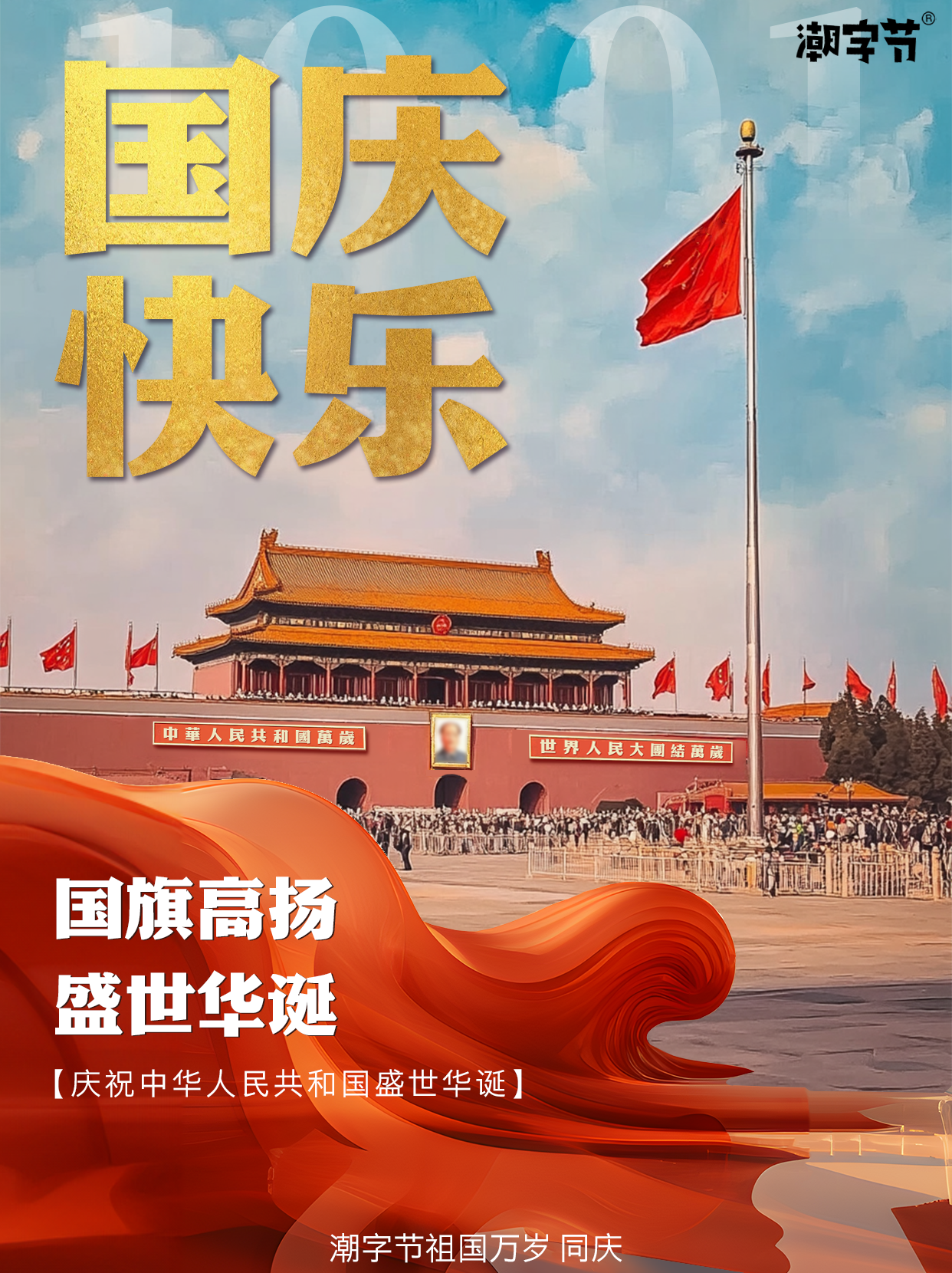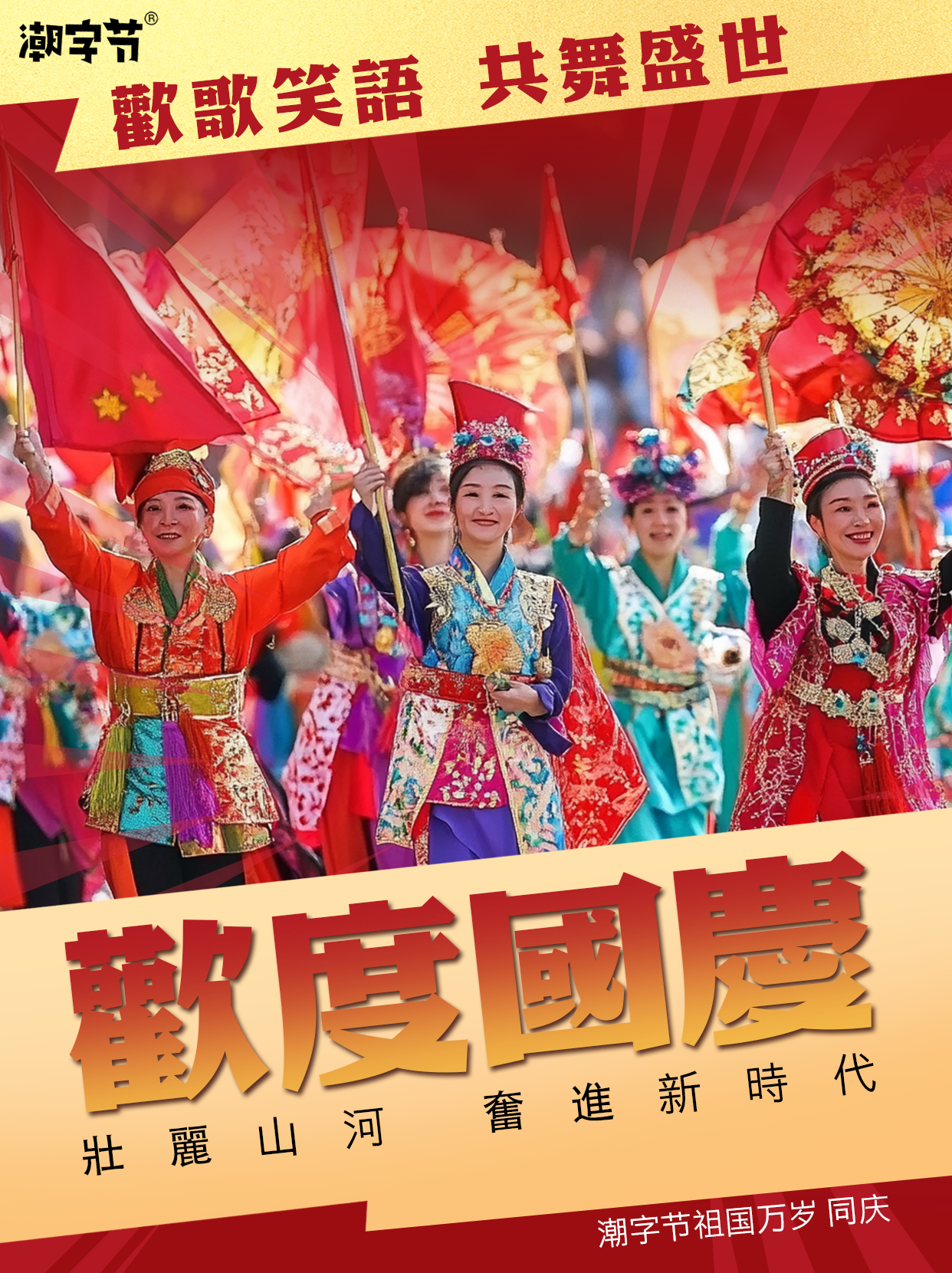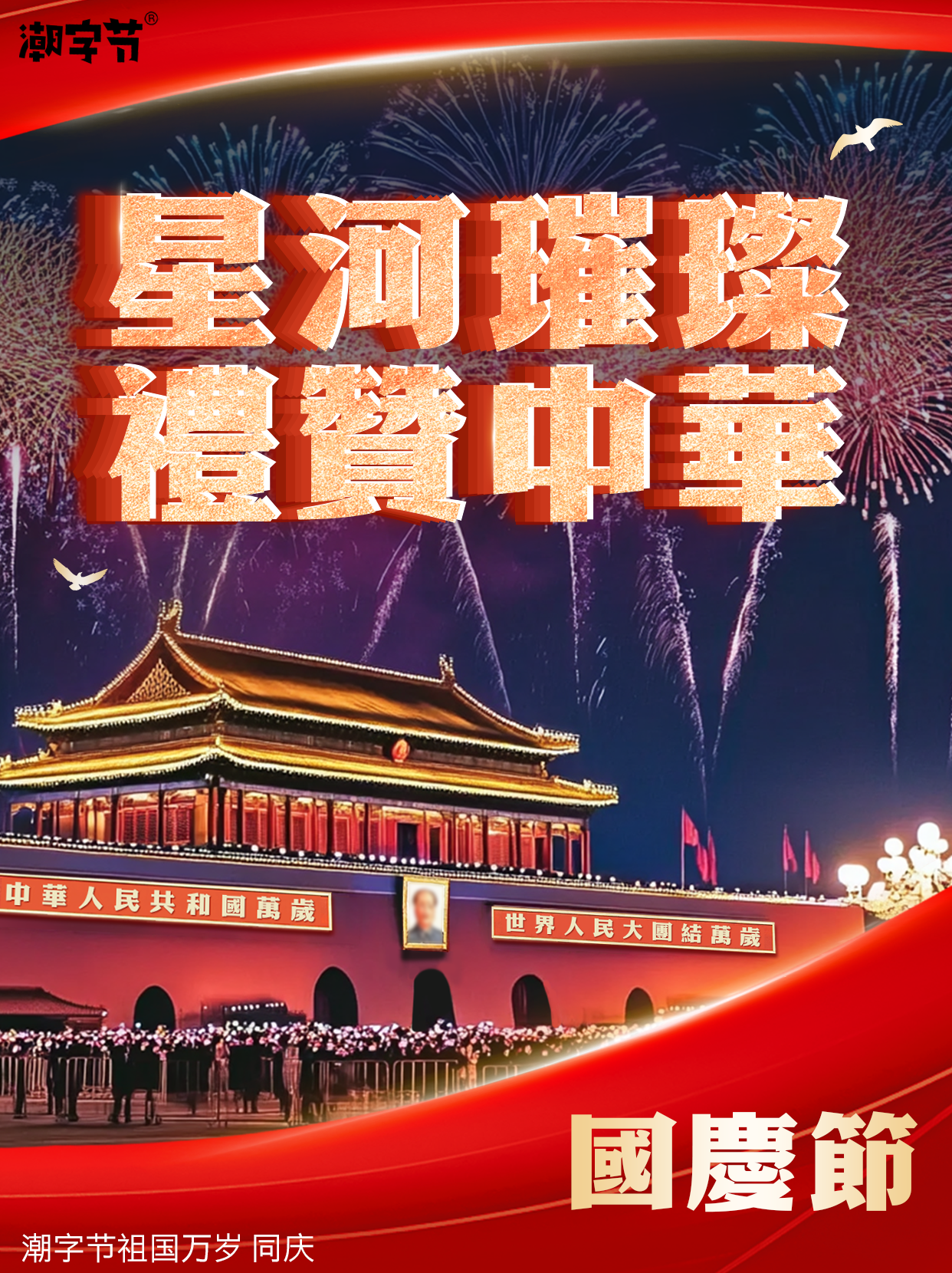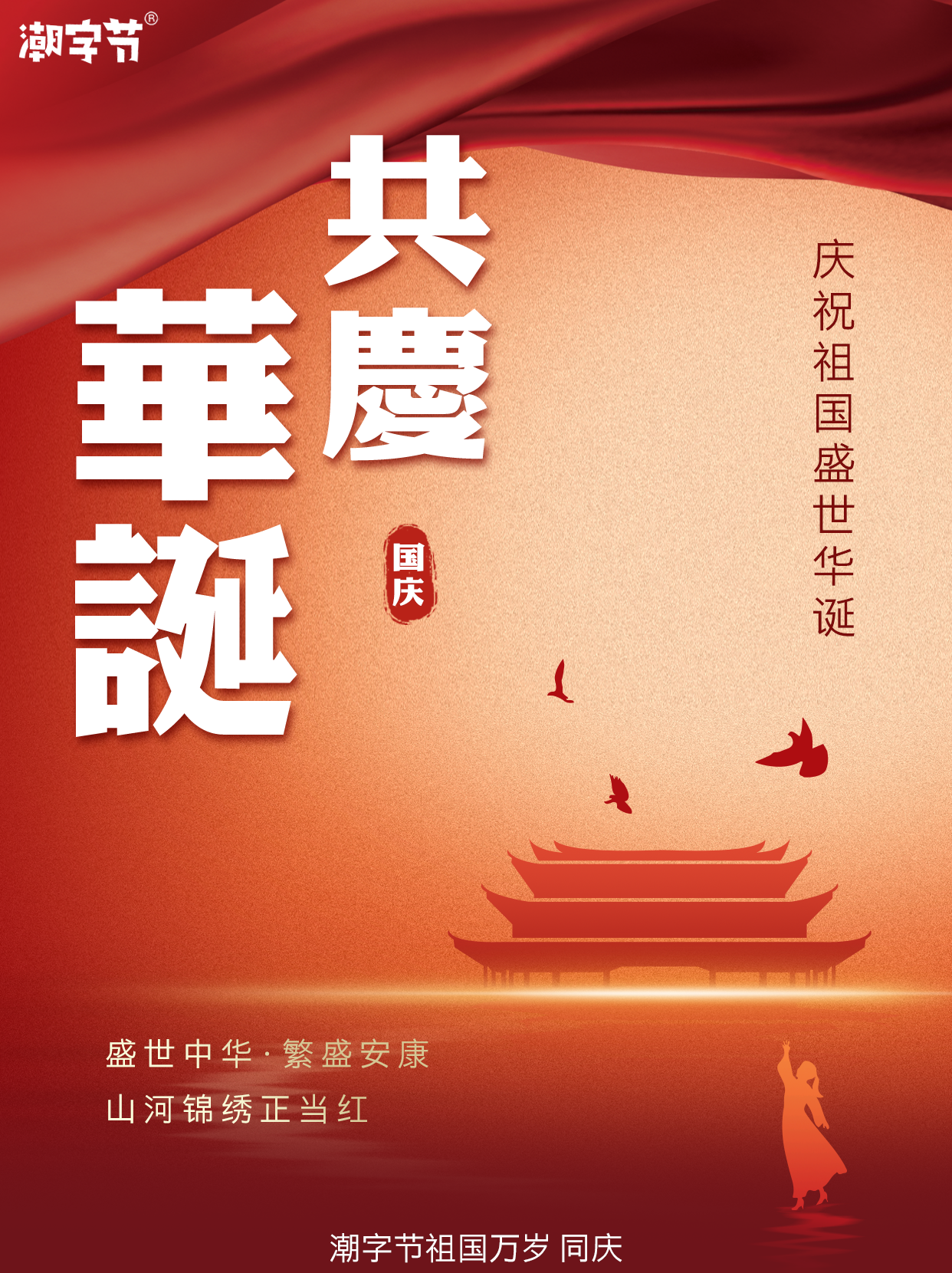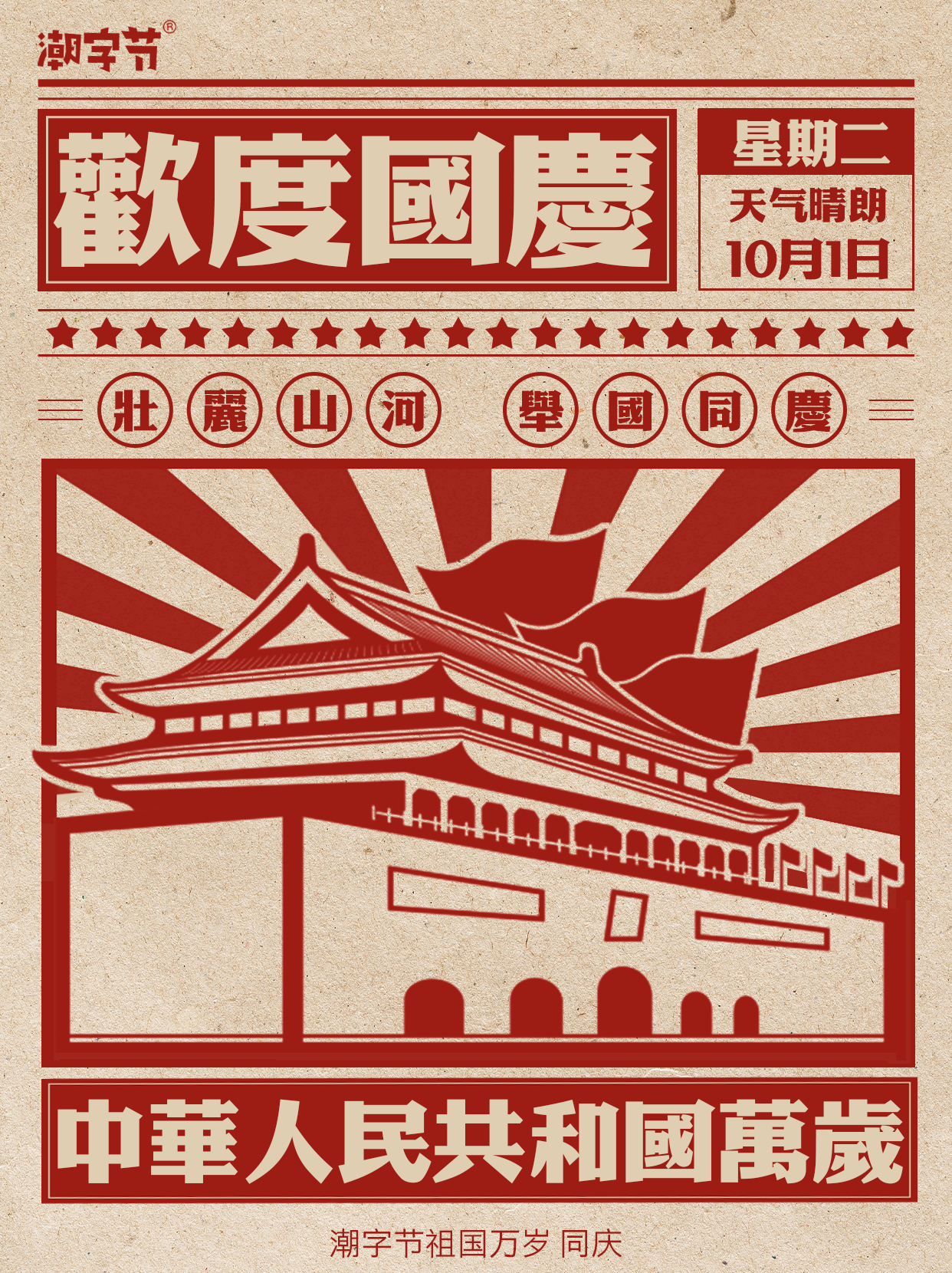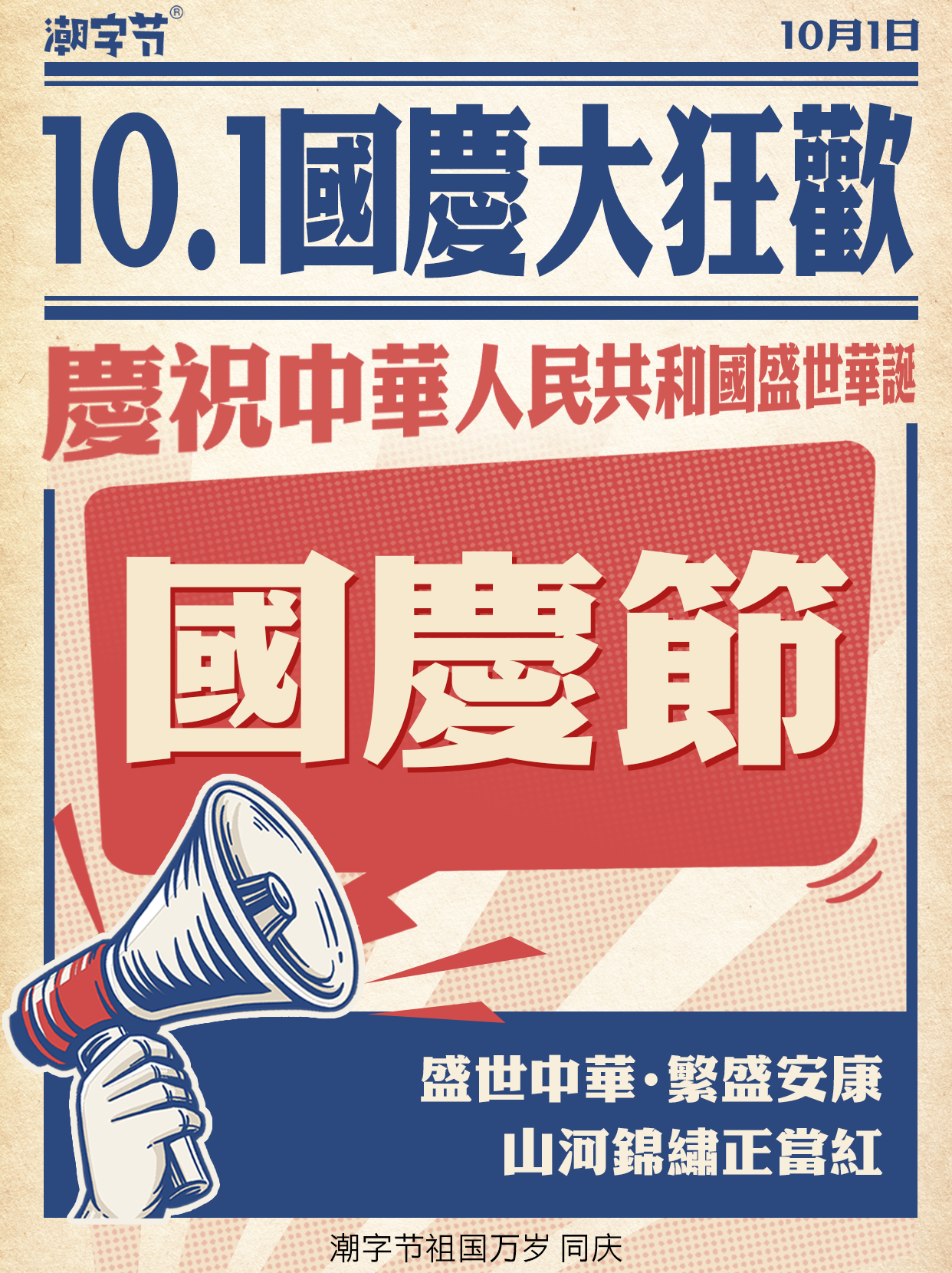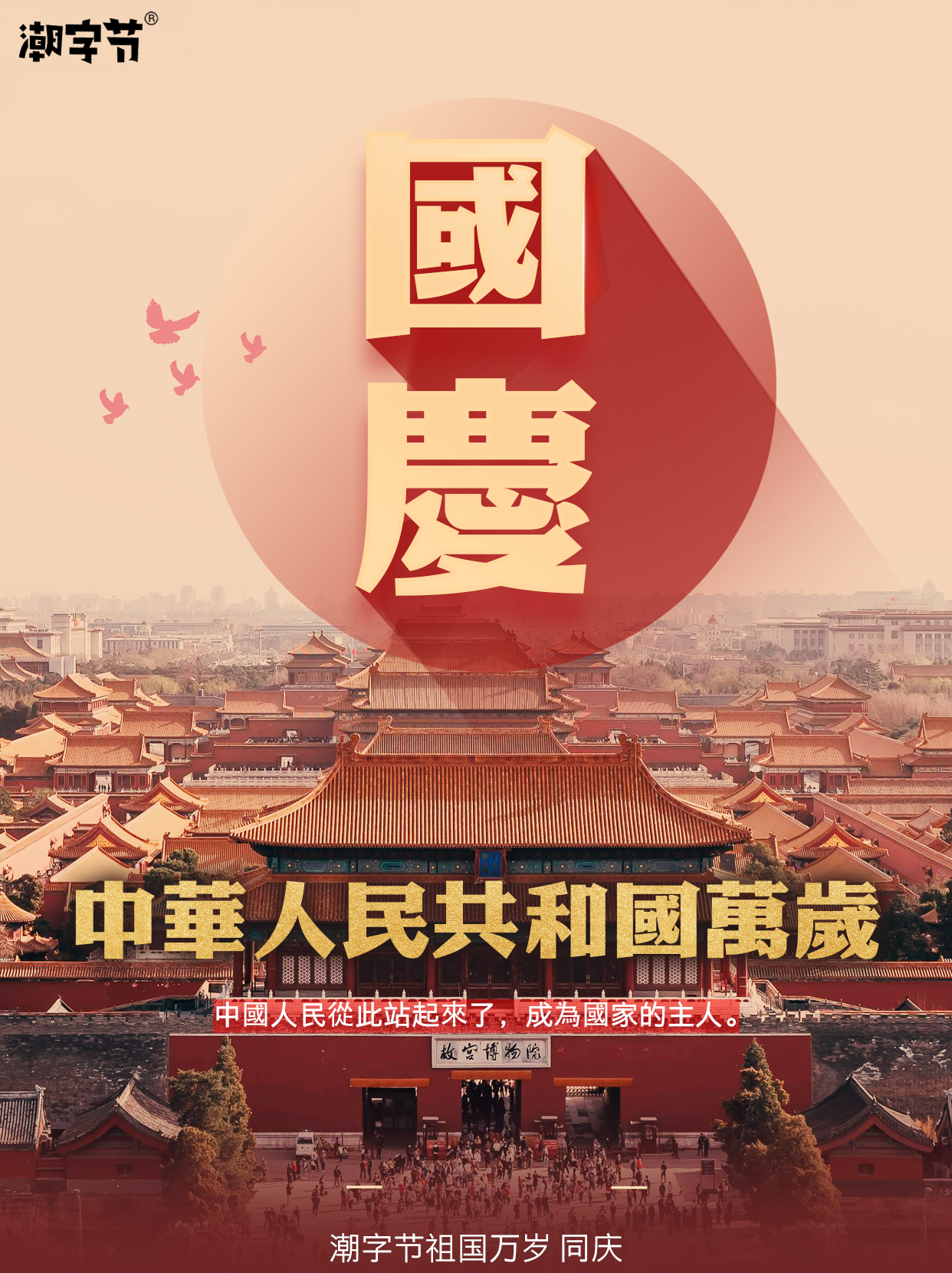
潮字节祖国万岁 同庆是一款将宋体的风韵与黑体的厚重相融合的标题体。
字形饱满,结构端正,迎面呈现出端庄的氛围,且其中宫开阔,整体非常稳重大气。笔画设计在保留宋体的人文感的同时,简化了起收笔画以及钩笔的细节,增强了年轻与现代感,同时加粗了横笔的粗细,减弱了粗细对比关系,使视觉上呈现出的力量感更加接近黑体。应用于国庆相关的节日海报、节日标语等场景中具有良好的视觉展现,传达浓厚的节日氛围和爱国情怀。